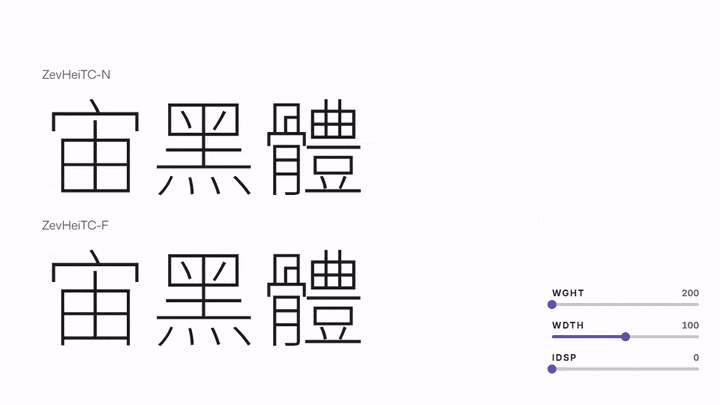
展示ZevHeiTc字体两种变体(-N和-F)的预览界面,包含重量、宽度和间距的调节滑块。
宙黑体是由昭源黑体改造而成的免费黑体字体,其字形风格与昭源黑体有所不同。
比较
以下是宙黑体与昭源黑体在字形上的差异对比:
1. 宙黑体对原昭源黑体中的汉字字形进行了“去掉笔脚”、“将笔尖的棱角磨平”、“去除喇叭口状的笔画特征”等处理,使得字形更具几何感。
2. 宙黑体的英文字形采用 Mona Sans 字体来呈现,这与昭源黑体所使用的 Source Sans 字体不同。
3. 得益于 Mona Sans 所具备的窄体和宽体字型,宙黑体也通过 wght 轴提供了 80%到 120%不等的字型宽度选项,从而让用户能够选择更多样的字型风格。
4. 宙黑体还提供了 IDSP 轴(即表意字字距调整轴),从而为汉字提供了更宽泛的字距选择。该功能的初衷是为了在需要缩小字宽时,能够对字距进行适当的补偿。
5. 宙黑体字在“拔脚”的处理上提供了两种变体:N 版采用“完全拔脚”的处理方式,而 F 版则保留字形底部作为支撑的“脚”的特征。
6. 宙黑体没有像昭源黑体那样提供“Text”版本以及与之对应的、可变字型的 PADG 轴和斜体。
命名
安装后的字体名称为 ZevHeiTC-[VARIANT],其中[VARIANT]可以是 N 或 F,分别代表“完全去掉底部笔画”和“保留底部笔画”两种字形变体。这两种字体都提供了对字重、字宽以及表意文字的间距进行调整的功能。
字体为那些不支持可变字型的应用程序提供了各种预设的静态项目。其命名规则如下:
ZevHeiTC-[變體] Dev [字重] [字寬] [表意文字字距]
以下是一些例子:
• ZevHeiTC-N 开发版
• ZevHeiTC-F 开发版 200
• ZevHeiTC-F 开发版 300 E20
• ZevHeiTC-F 开发版,C80,A5
各部份的説明如下:
字重 (wght)
字体提供 200 (最细) 到 900 (最粗) 的字重选项,在静态项目中使用时,字重直接用数字表示。以下是一些常见的字重名称供参考:
字重值常见字重名名称
200ExtraLight
300光明
350正常
400定期/常规
500中等水平
600半粗体
700加粗字体
900很重
其中,400 属于预设的字体粗细。在某些应用程序中,系统会忽略该字体粗细值,仅显示字体名称(如 ZevHeiTC-N Dev )。而 700(粗体)实际上是与 400(常规)相关联的粗体效果。在某些应用程序中,必须通过“粗体”样式来切换才能使用该效果;该选项不会显示在字体菜单中。
字符宽度 (wdth)
字体提供 75% 到 125% 的字体宽度选项,默认值为 100%。 字体定义了以下静态属性:
名称数值
C8080% 的原始宽度
C9090% 宽度
(空白)原始格式 (即 100% 宽度)
E10110% 宽度
E20120% 宽度
“Cx” 可以理解为“收窄到 x%”,而“Ex”可以理解为“扩大到 x%”。
字符间距 (IDSP)
这用于调整表意文字(汉字)的字距。可选值范围为 0 到 500。当字距增加 200upm 时,意味着字距增加了 20%。默认值为 0,表示不增加字距。
名称数值
(空)原字间距
A5增加 5upm 字距(即增加 5upm 增距)
A10增加 10upm 的字符间距(即增加 5upm 的间距)
静态项目中增加字距选项仅会在使用窄型字體(C80、C90)时出现。
请注意
• “宙黑体”字体,其字形宽度范围在 80%到 120%之间,这是一种自动调整,无需人工干预,可能存在一些缺陷。